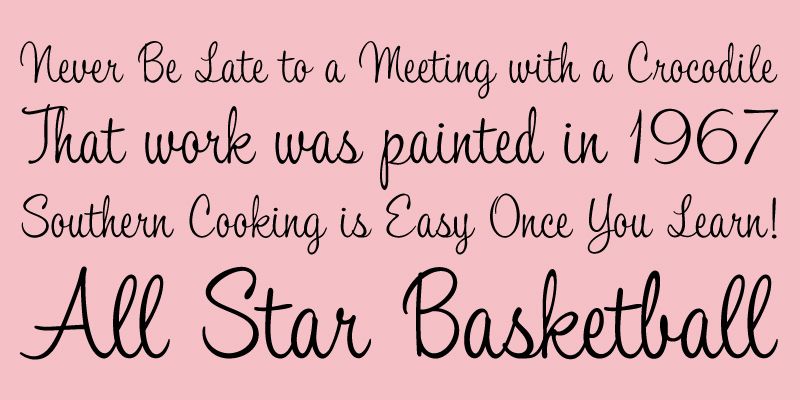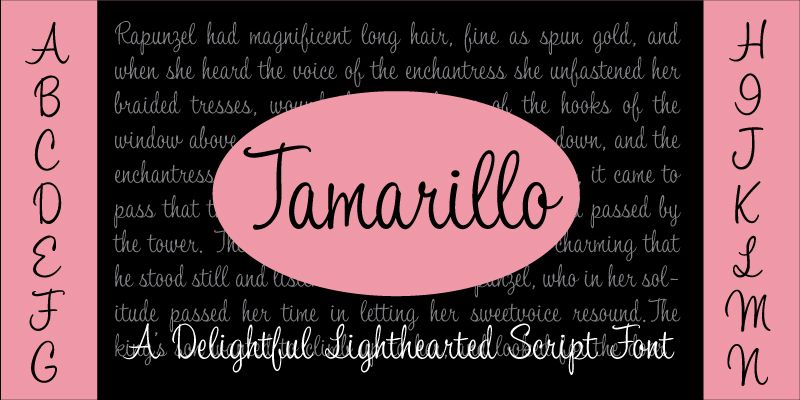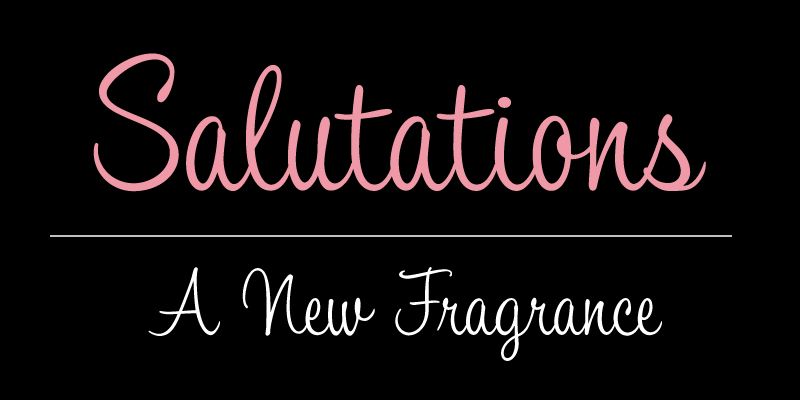
Tamarillo ist eine lässige, aufrechte Schriftart, die aus einer älteren Schriftart digital mit Fototypisierung wiederbelebt wurde. Sie enthält eine kleine Anzahl von Alternativzeichen und Ligaturen, um den reibungslosen Fluss der Buchstaben zu erhalten.